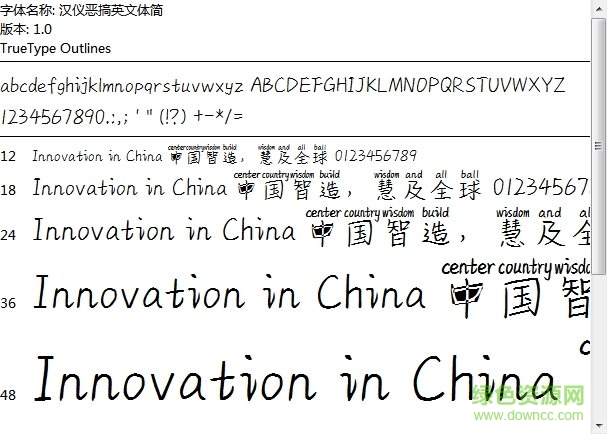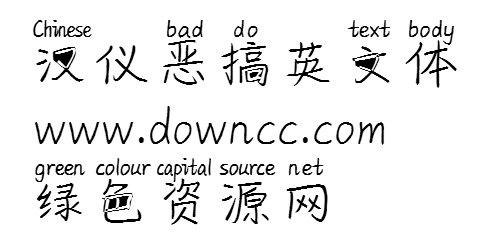
惡搞英文體是一款十分Q萌逗趣的藝術(shù)手寫(xiě)字體,結(jié)構(gòu)類(lèi)似拼音字體,在中文漢字的上方都采用了英文注釋?zhuān)x起來(lái)十分搞笑,還能幫助大家記憶單詞,快來(lái)綠色資源網(wǎng)試試吧!
只怪我詞匯量不enough,智能夾雜Chinese來(lái)湊數(shù)。
惡搞英文體出自漢儀字體庫(kù),在手機(jī)qq上手法,中文書(shū)寫(xiě)流暢而簡(jiǎn)練,而每個(gè)漢字對(duì)應(yīng)一個(gè)簡(jiǎn)單的英文釋義單詞,讓你的文字更有國(guó)際范,當(dāng)然這種翻譯并不是專(zhuān)業(yè),只是為了搞笑、整蠱而已。